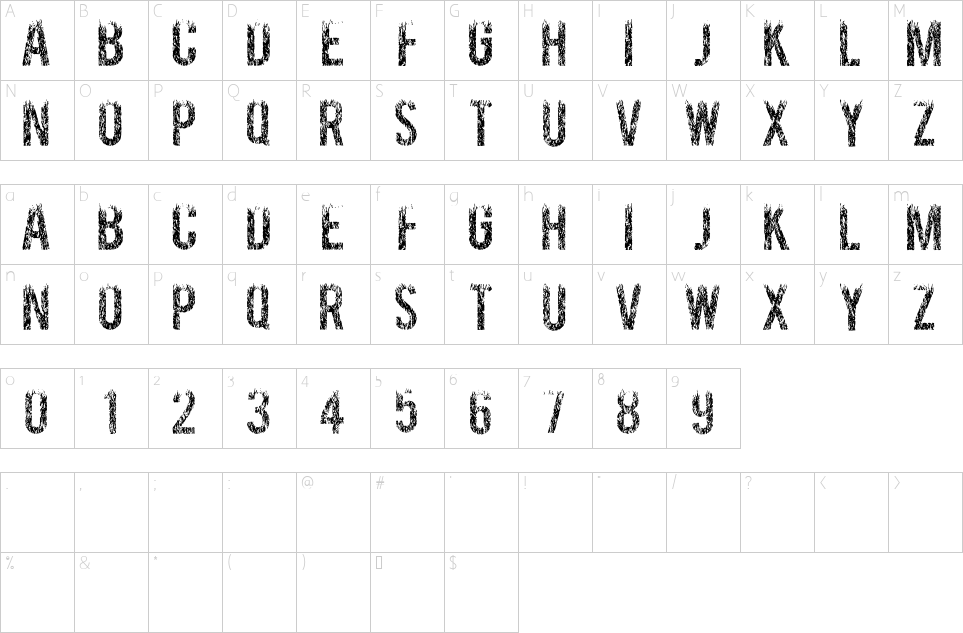
A Grass Event Font é uma opção gratuita e elegante para aqueles que buscam uma fonte moderna para seus eventos ou projetos digitais no Windows e Mac. Desenhada pelo designer desconhecido Xerographer Fonts, esta font é ideal para criar um visual atraente em sua próxima apresentação de PowerPoint ou adicionar um toque especial à sua identidade digital. Com sua aparência fresca e simples, a Grass Event Font se destaca pela facilidade na qual combina com outros estilos. Seja você designer gráfico profissional ou iniciante, essa fonte é uma ótima opção para quem está em busca de um estilo contemporâneo sem o compromisso de custos maiores. Descubra por si mesmo o charme desta fonte e prepare-se para criar textos que chamem a atenção, enquanto economiza tempo e dinheiro ao escolher uma fonte gratuita.